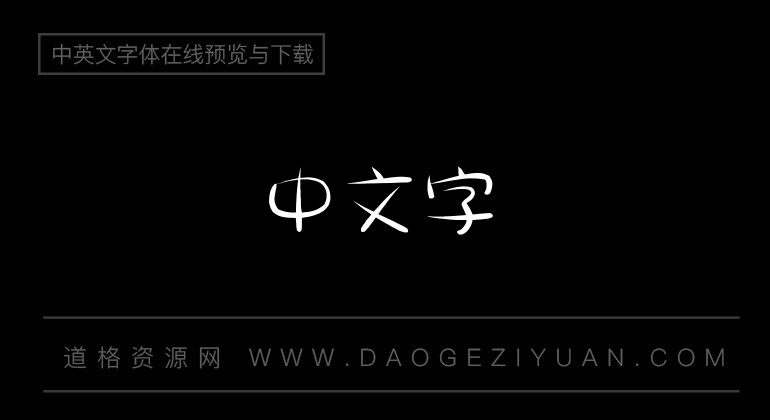
金梅美工大头字体
金梅美工大头字体是一款简洁大气的字体,它具有清新活泼的风格,极具表现力,可以让文字更加有趣,更有视觉冲击力。金梅美工大头字体的字体结构特别简单,比较容易阅读,但又不失精致,字符间的间距也很合理,可以让文字更有层次感。此外,金梅美工大头字体还具有柔和的曲线,可以让文字更加柔和,不显得太硬,更易被消费者接受。
金梅美工大头字体是一款非常不错的手写艺术字体,具有很好的视觉感,适合于文化类的宣传设计、商业类品牌的广告和产品包装设计以及个性化文字排版等较多场景。
金梅美工大头字体字符映射图